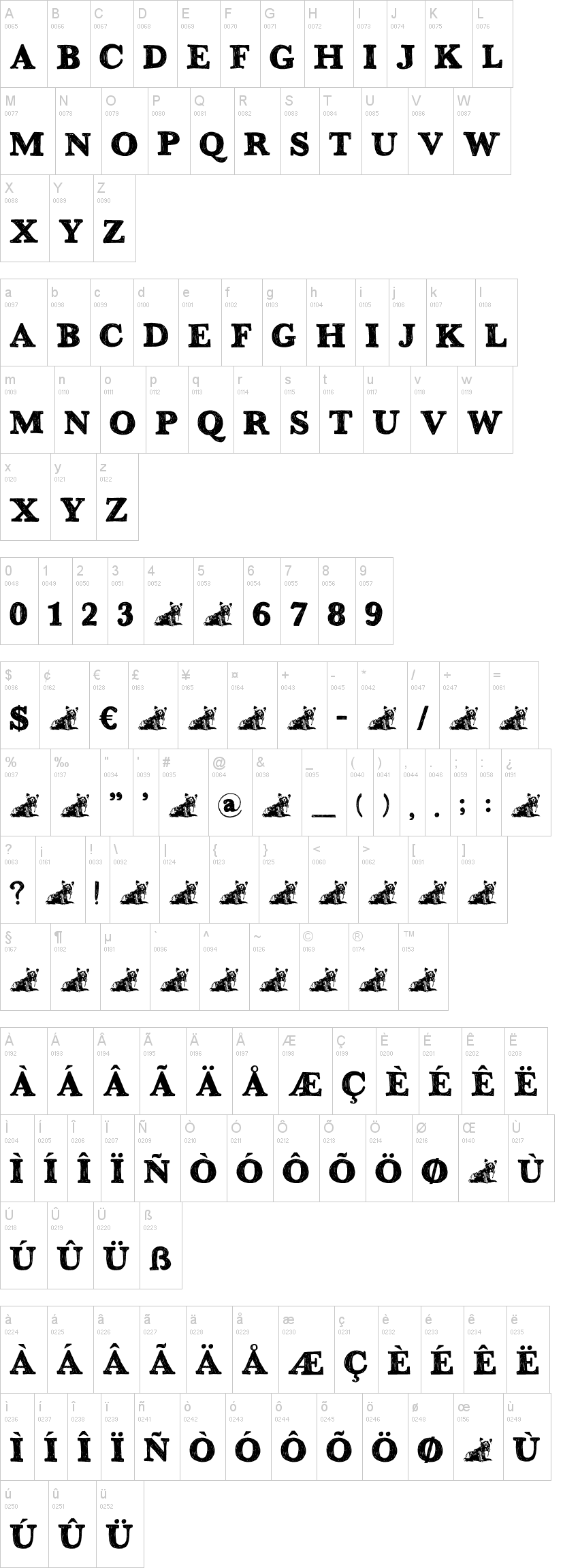
DK Greyfriars
DK Greyfriars 是一款具有英伦风格的字体,它具有细节丰富的笔画,比较柔和的线条,以及细微的曲线,使其看起来更加优雅和典雅。它具有文艺复兴时期的英国风格,使其在文字中具有更多的历史感。它的字体特征突出,使用起来更加灵活,可以用于宣传海报、书籍封面、品牌标识、报纸标题等各种应用场景中。
DK Greyfriars是一款非常不错的手写艺术字体,具有很好的视觉感,适合于文化类的宣传设计、商业类品牌的广告和产品包装设计以及个性化文字排版等较多场景。